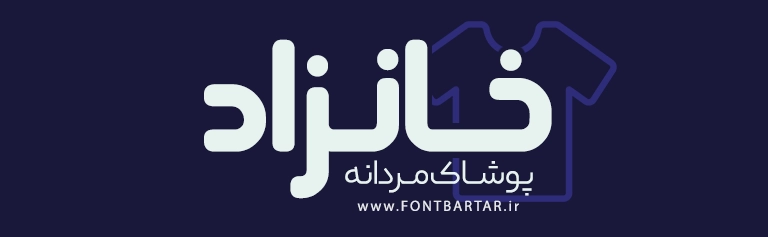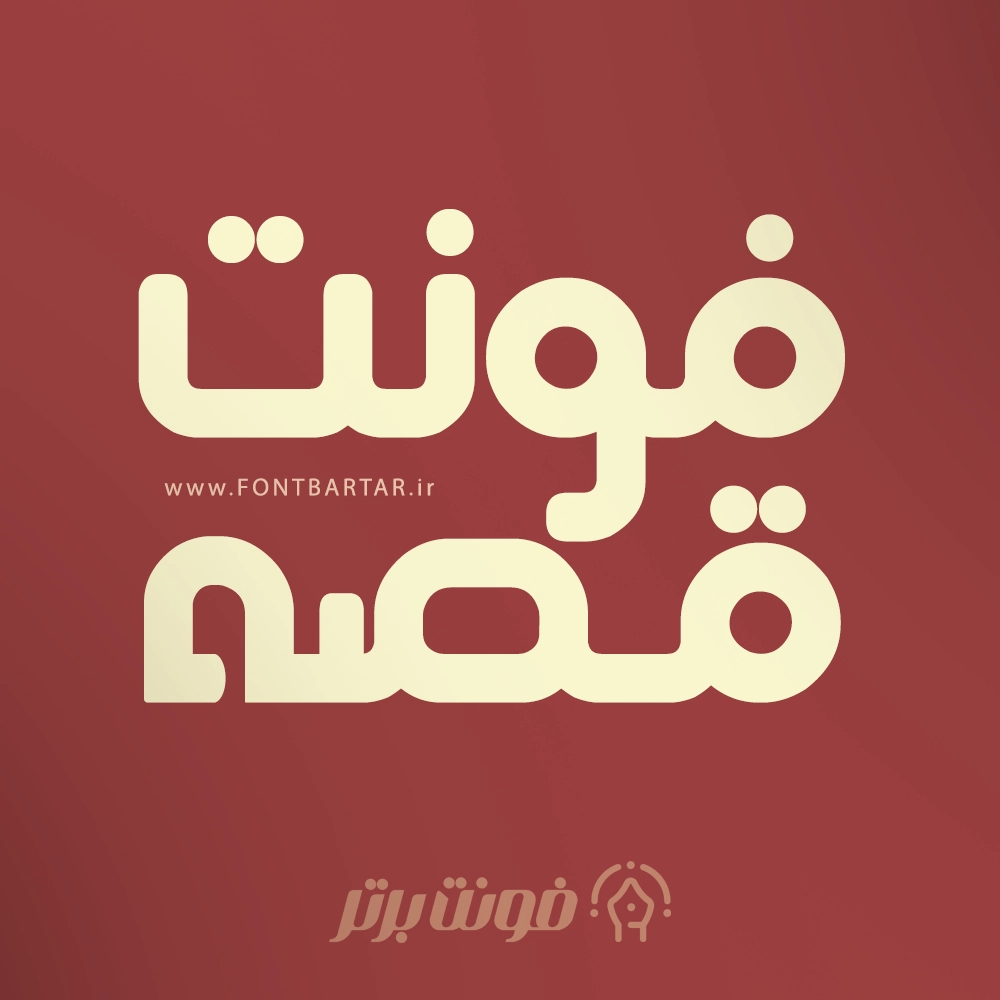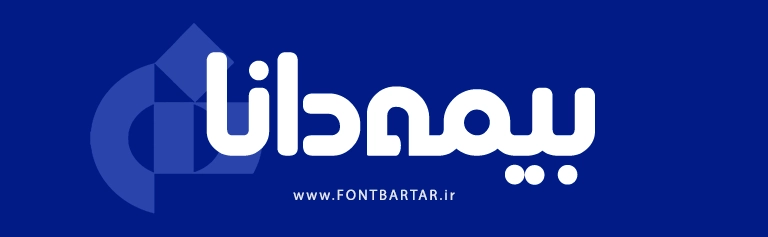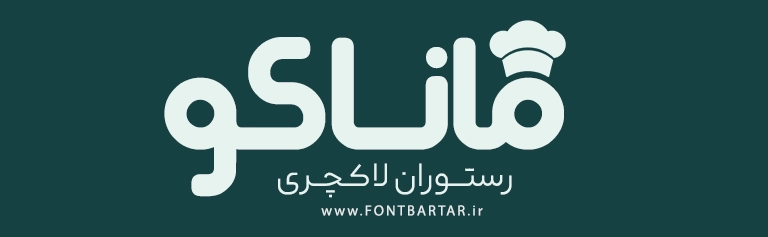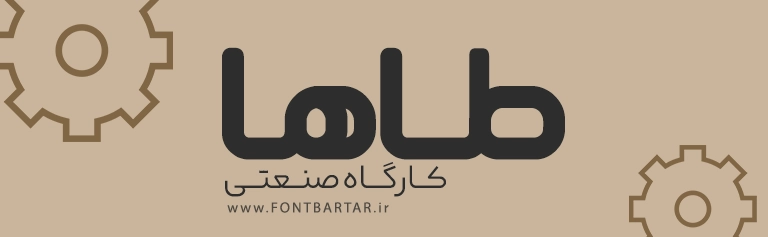
فونت خاص قصه
فونت قصه
Ghese Font
فونت قصه
فونت تایپوگرافی ، فونت لوگوتایپ – فونت قصه
فونت قصه یکی از فونت‌های جدید و خلاقانه فارسی است که با الهام از فرم‌های نرم و هندسی طراحی شده و مناسب انواع طراحی‌های مدرن و دیجیتال است. اگر به دنبال فونتی هستید که در عین سادگی، حس گرما و صمیمیت را منتقل کند، فونت قصه دقیقاً همان چیزی است که نیاز دارید.
فونت خاص فارسی قصه با ساختار دایره‌ای و حروف گرد، حال‌و‌هوای دوستانه و قابل خواندن دارد و در عین حال برای لوگو، پوستر، تایپوگرافی و بنرهای تبلیغاتی فوق‌العاده عمل می‌کند.
فونت خاص قصه که یک فونت حرفه ای مناسب طراحی های گرافیکی می باشد ، شما می توانید از فونت فارسی قصه در کارهای گرافیکی خود استفاده کنید ،این فونت به دلیل بولد بودن آن در تصاویر می توان در چاپ بنر قابل توجه باشد. شما با استفاده از فونت قصه می توانید یک طراحی به یاد ماندنی داشته باشید.
فونت قصه
فونت جدید و خاص قصه
بهترین فونت فارسی قصه
چرا فونت قصه را انتخاب کنیم؟
فونت قصه یک انتخاب حرفه‌ای برای طراحانی است که به دنبال تعادل بین سادگی و زیبایی هستند.
استفاده از این فونت باعث می‌شود طراحی شما:
• حس خلاقیت و نوآوری را منتقل کند
• ظاهری مدرن و تمیز داشته باشد
• برای کاربران فارسی‌زبان کاملاً خوانا و جذاب باشد
• در هر پروژه‌ای (دیجیتال یا چاپی) قابل اعتماد باشد